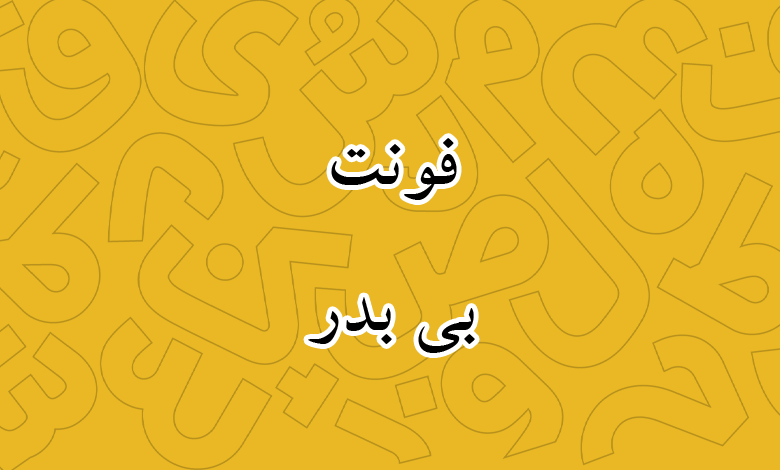
فونت بی بدر (B Badr)
فونت بی بدر یا بدر (به انگلیسی: B Badr) بر پایه خط ثلث طراحی شده که تا حدودی شباهتهای جزئی از خط نسخ امروزی را با خود به همراه دارد. این فونت در دهه ۷۰ در دو وزن بولد و معمولی طراحی شده است. در ادامه به لینک دانلود رایگان فونت بی بدر دسترسی داشته و با قابلیتهای بیشتر این فونت آشنا خواهید شد.
فونت بدر از سری فونتهای بی است که توسط شرکت برنا رایانه طراحی و تولید شده است. این فونت دارای ساختاری ساده و در عینحال خوانا است که برای متون بلند کاربردی بوده و با توجه به داشتن نسخه بولد، میتوانید در عناوین نیز از این قلم استفاده کنید.
آخرین نسخه از فونت B badr در سال ۱۳۷۹ به ورژن ۲.۰۱ آپدیت شده است که دارای در هر دو نسخه Bold و Regular از حالت OutLine نیز پشتیبانی میکند که میتوانید این سبک را به کمک نرمافزارها بر روی نوشتههای خود اعمال کنید.
پیشنمایش و امکانات فونت بی بدر (B Badr)
فونت بی بدر از نظر ظاهری شباهتهای زیادی به دو فونت همخانواده خود یعنی فونت لوتوس و فونت فارسی زر دارد؛ با این تفاوت که ساختار برخی حروف تغییر یافته و فونت ظاهری فشردهتر از نظر طولی دارد. در این فونت حروف قائم همچون «الف، ط، ظ، ل» دارای کشیدگی بیشتری هستند که مبنای اصلی خط ثلث محسوب میشود.
حروف دیگری نظیر «ن، ل، س، ش، ص، ض» که دارای گودی هستند، ساختاری جمعتر داشته و زوایای این بخش فشردهتر بهنظر میرسد که میتواند به خوانایی بیشتر متن کمک کند.
فونت بی بدر برای استفاده در متون طولانی بسیار کاربردی است و با توجه به سبکی که در ترکیب حروف و کلمات مختلف از خود برجای میگذارد، میتواند در خوانایی به خواننده کمک بیشتری کند تا دچار خستگی چشم نشود. هرچند که امروزه خطهایی که بر پایه هندسه و نسخ طراحی شدهاند، از این نظر بهتر عمل میکنند. اما فونت B Badr برای دهه هفتاد با چنین ساختاری گزینهای کاربردی بود.
فونت بدر از زبان فارسی پشتیبانی کاملی دارد و مختص این زبان طراحی شده است. این فونت کاستی موجود در قلمهای لوتوس و زر را از بین برده که در آنها اعداد «۴۵۶» دارای تایپ عربی بودند. هرچند که انتظار میرفت عدد صفر نیز تو خالی طراحی شود.
برای استفاده از فونت B badr در سایر زبانهای عربی و اردو محدود به حروف مشترک با رسمخط فارسی خواهید بود و حروفی مثل «ک، ی، ه» در عربی یا «ﮧ، ﮩ، ے» اردو در این قلم پشتیبانی نمیشوند.
از فونت بولد بی بدر میتوانید در عناوین استفاده کنید. نسبت به وزن معمولی (Regular) دارای ضخامتی است که در سرتاسر حروف بیشتر شده است تا فونت ظاهری نمایشی داشته باشد. از این وزن میتوانید برای فونت عناوین کتاب یا فونت تیتر در روزنامه و مجلات استفاده کنید که با هدف جلب توجه مخاطب مورد استفاده قرار میگیرند.
فونت بدر فارسی معمولی هم برای استفاده در متون بلند مناسب است که بیشترین کاربرد آن تا بهامروز در صنعت چاپ بوده است. از چاپ کتاب گرفته تا مجلات، روزنامهها و حتی بیلبوردهای تبلیغاتی که در دهههای ۷۰ و ۸۰ مورد استفاده قرار میگرفتند.